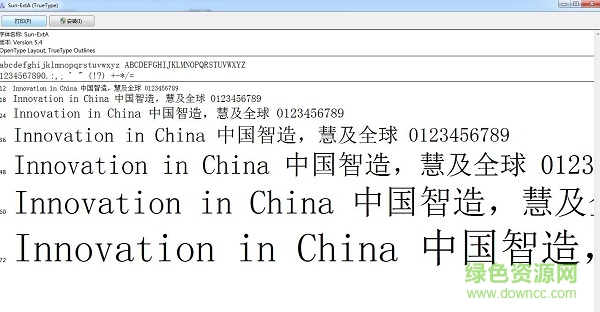
sun-exta
sun-exta是什么字體?sun-exta字體是一款由中易推出的宋體字體,干凈優(yōu)雅,線條纖細(xì),有著極強(qiáng)的用性,打印效果非常清晰,歡迎大家免費(fèi)下載!
sun-exta字體特點(diǎn)
字形清秀、古樸,風(fēng)格典雅,與書宋體特點(diǎn)相似,是印刷界中較為穩(wěn)重的正文字,實(shí)用性很強(qiáng)!